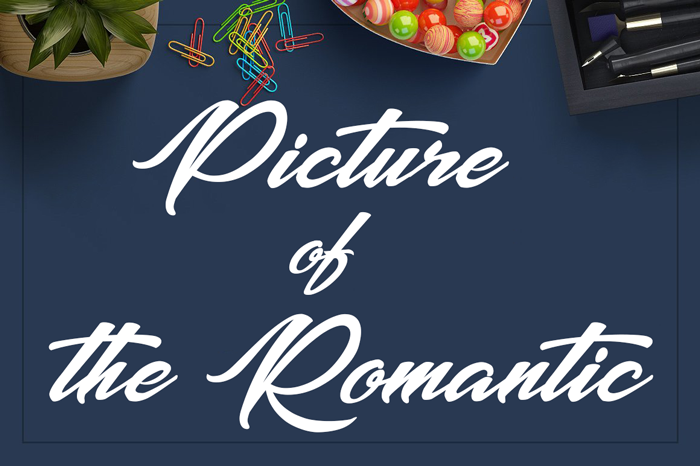
Picture of the Romantic Font – Download Grátis
A fonte ‘Picture of the Romantic Font’ é uma elegante escolha para qualquer projeto que deseja transmitir sensibilidade e romantismo através do texto. Escrevendo com a mão, essa fonte oferece um toque delicado ao combinar linhas curvas suaves e traços finos, criando um apelo romântico que se ajusta perfeitamente para gráficos de aniversário, cartões personalizados ou até mesmo ilustrações de livros antigos. Com a Octotype como o designer responsável, você está lidando com uma fonte cuidadosamente projetada para oferecer tanto estilo quanto facilidade de uso. Seja um registro romântico ou qualquer outra aplicação onde desejar serem vistos como delicado e amoroso – essa fonte tem tudo que precisa. Descubra a sensibilidade da escrita à mão com Picture of the Romantic Font, uma escolha ideal para seus projetos gráficos românticos.